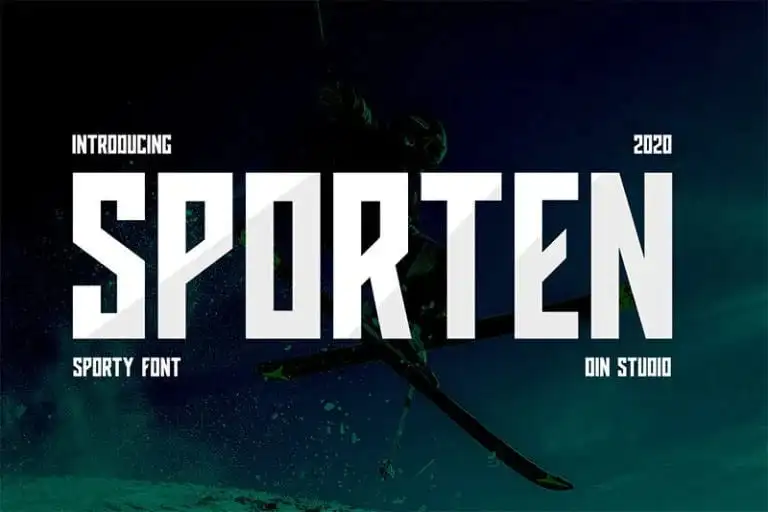
A Sporten Display Font é uma elegante escolha para aqueles que buscam um toque vintage em suas aplicações digitais. Desenhada manualmente com inspiração em esportes, esta fonte atinge a perfeita dose de sofisticação e naturalidade que os projetos desportivos exigem. Ela é ideal não apenas para uso profissional, mas também para qualquer aplicação que exija um visual vívido e imediato, como impressão ou identificação de marca. Este font foi criado pelo Din Studio e oferece uma experiência única, combinando a paleta vibrante dos esportes com o charme retro da arte manual. Não só é perfeito para criar camisetas de time ou cartazes desportivos, mas também pode ser facilmente adaptada para uso em postagens de mídia social, artigos esportivos e até mesmo como citações personalizadas, tornando-o uma fonte versátil que se adapta a uma variedade de usos. Com sua inspiração clara na cultura desportiva, é um complemento perfeito tanto para aqueles que valorizam o design digital quanto para os amantes dos esportes.